三省堂 例解小学国語辞典 第七版/三省堂 例解小学漢字辞典 第六版
三省堂は、モリサワが開発した「UDデジタル教科書体」を辞書ではじめて採用した、小学生向け辞典の最新改訂版「三省堂 例解小学国語辞典 第七版」「三省堂 例解小学漢字辞典 第六版」を2019年11月20日(水)より発売した。
「UDデジタル教科書体」は、学習指導要領に基づいた、より良い学びに適した字形の書体で、学力向上にもつながると期待されている。
三省堂は、辞典の見出し語を中心とした視認性の向上と、書写学習での有用性を両立することが可能であり、小学生向け辞書での使用に適した書体であることから採用に至ったとのこと。
三省堂「例解小学国語辞典 第七版」「三省堂 例解小学漢字辞典 第六版」で「UDデジタル教科書体」を採用した経緯
従来の小学生向け辞書では、見出し語にゴシック体やアンチック体・教科書体などの書体が使用されてきた。ゴシック体には、文字の太さが肉厚かつ均一であり、視認性が高く、教科書体に比べ使用部分が引き立つという長所があるが、ゴシック体は印刷用の書体であるため、「手書きの場合と形状が異なる」「運筆がわかりにくい」という短所がある。小学生が書写を正しく身につけるという観点で考えた場合、ゴシック体の採用についてはメリットよりデメリットのほうが大きいことが懸念されるため、三省堂の小学生向け辞書では、学校現場の教師の意見を踏まえたうえで、見出し語にはアンチック体・教科書体を使用してきた。
2019年11月20日(水)より発売する最新改訂版の「三省堂 例解小学国語辞典 第七版」「三省堂 例解小学漢字辞典 第六版」では、モリサワが開発した「UDデジタル教科書体」を、辞書の見出し語ほか熟語解説など主要部分にはじめて採用した。
「UDデジタル教科書体」は多様な子どもたちの見え方に配慮された、太さの強弱を抑えたデザインでありつつ、手の動きを重視し運筆の向きがわかるように工夫された、子どもたちの学びに適した字形です。これにより、見出し語を中心とした視認性の向上と、書写学習での有用性を両立することが可能になる。さらに、「UDデジタル教科書体」は正確さを保ちながら読めることが実証されており、辞書がより見やすく、読みやすく、さがしやすくなるばかりではなく、学力向上にもつながると期待されている。
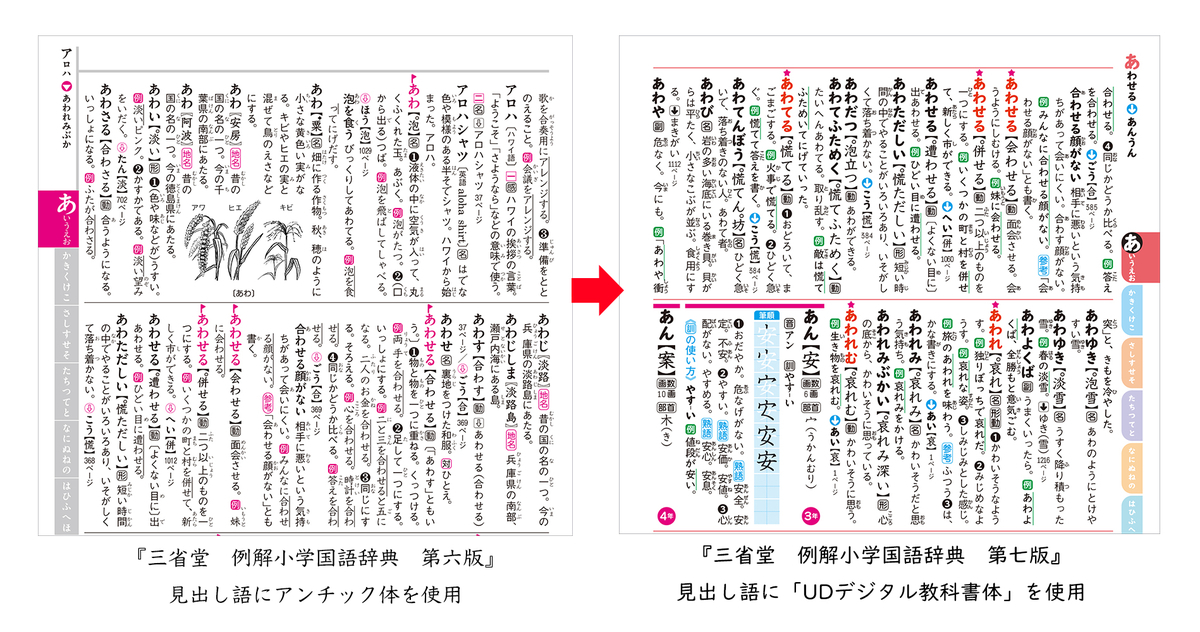
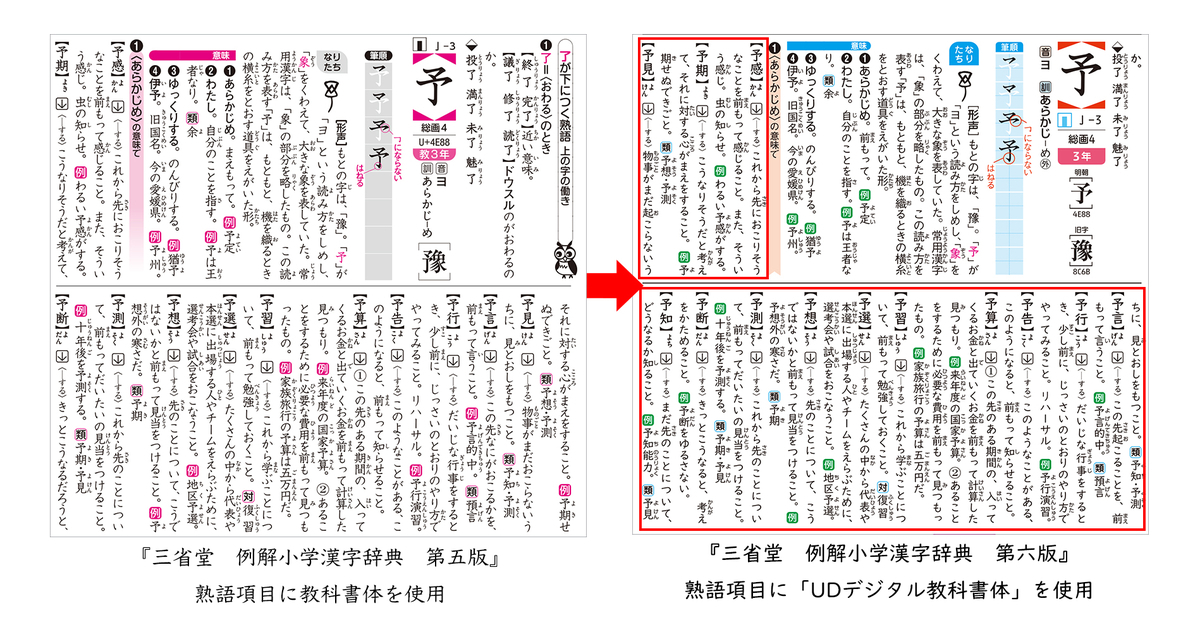
株式会社モリサワ「UDデジタル教科書体」の特長
・筆書きの楷書ではなく硬筆やサインペンを意識し、手の動きを重視した教科書体。
・書き方の方向や点・ハライの形状を保ちながらも、太さの強弱を抑えたデザインで、ロービジョン(弱視)、ディスクレシア(読み書き障害)に配慮。
・同じ部首や同系列の構成要素を持つ漢字字形をルール化し、バラツキを無くすことによって、ひとつの書体としてのデザインを統一。
・最近では、検定教科書やタブレットの教材などに多く採用されている信頼ある書体。
・「UDデジタル教科書体」がどれほど有効であるかを確認するため、奈良県生駒市と株式会社モリサワが共同で2019年2月14日に小学生116名とともに実験が行われ、実験の結果、「UDデジタル教科書体」のほうが正確さを保ちながら読めることが実証された。「UDデジタル教科書体」は、教育における合理的配慮に対応しているだけでなく、すべての児童にとって学習意欲の向上や学力向上につながると期待されている。
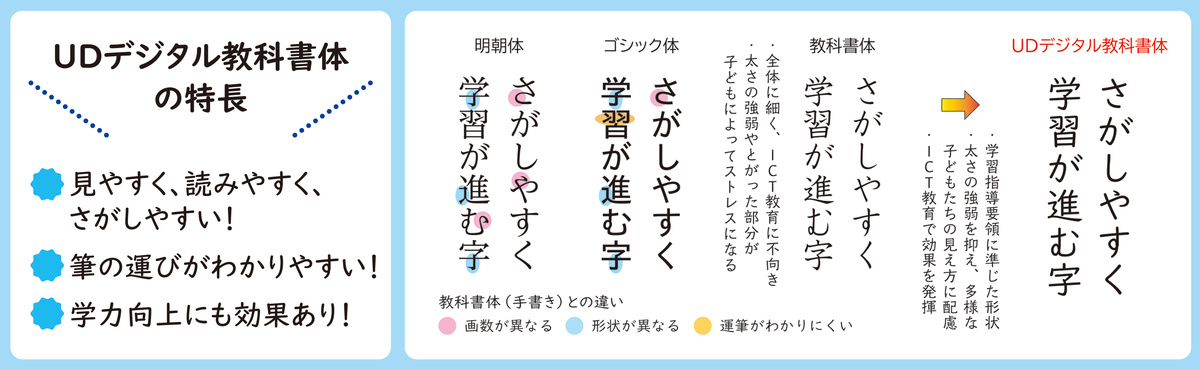
三省堂 例解小学国語辞典 第七版
オールカラーで見やすい紙面。さがしやすくて読みやすいUDデジタル教科書体を、辞書ではじめて使用。豊富なコラムや用例・図版に加え、すべての漢字にふりがな付きで、1年生からの学習に最適。各社教科書などから新たに1000語を収録。新学習指導要領にも対応。「百人一首」「新いろはがるた」ポスター付き。
三省堂 例解小学漢字辞典 第六版
オールカラーで見やすい紙面。読みやすくて分かりやすいUDデジタル教科書体を辞書ではじめて使用。総ふりがなで、1年生から使える。類書中最大級の親字3200字。漢字説明と意味別熟語説明で、漢字を楽しくはば広く学習。運筆がわかる筆順、故事成語・使い分けなどコラムも充実。さくいんになる二大特典つき。